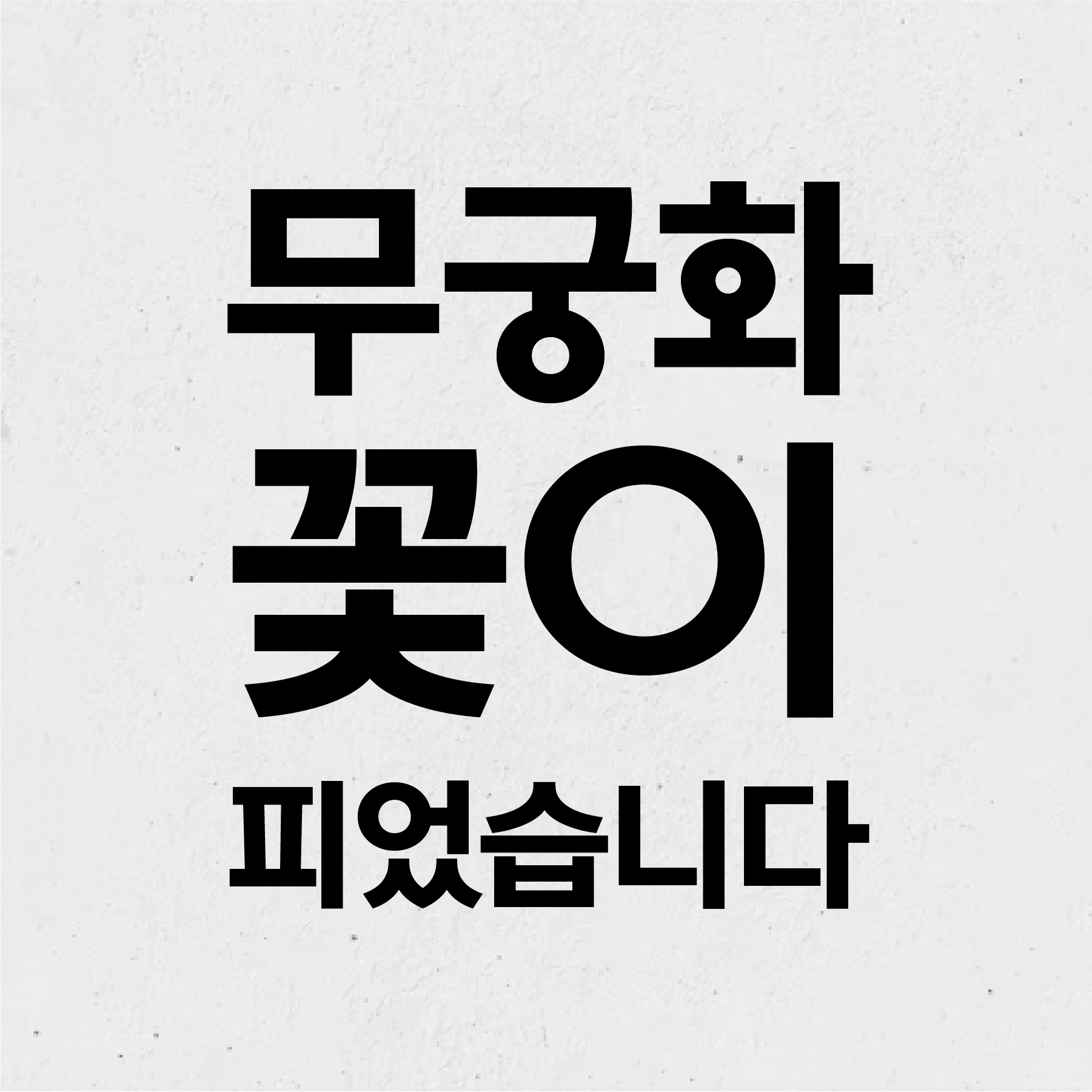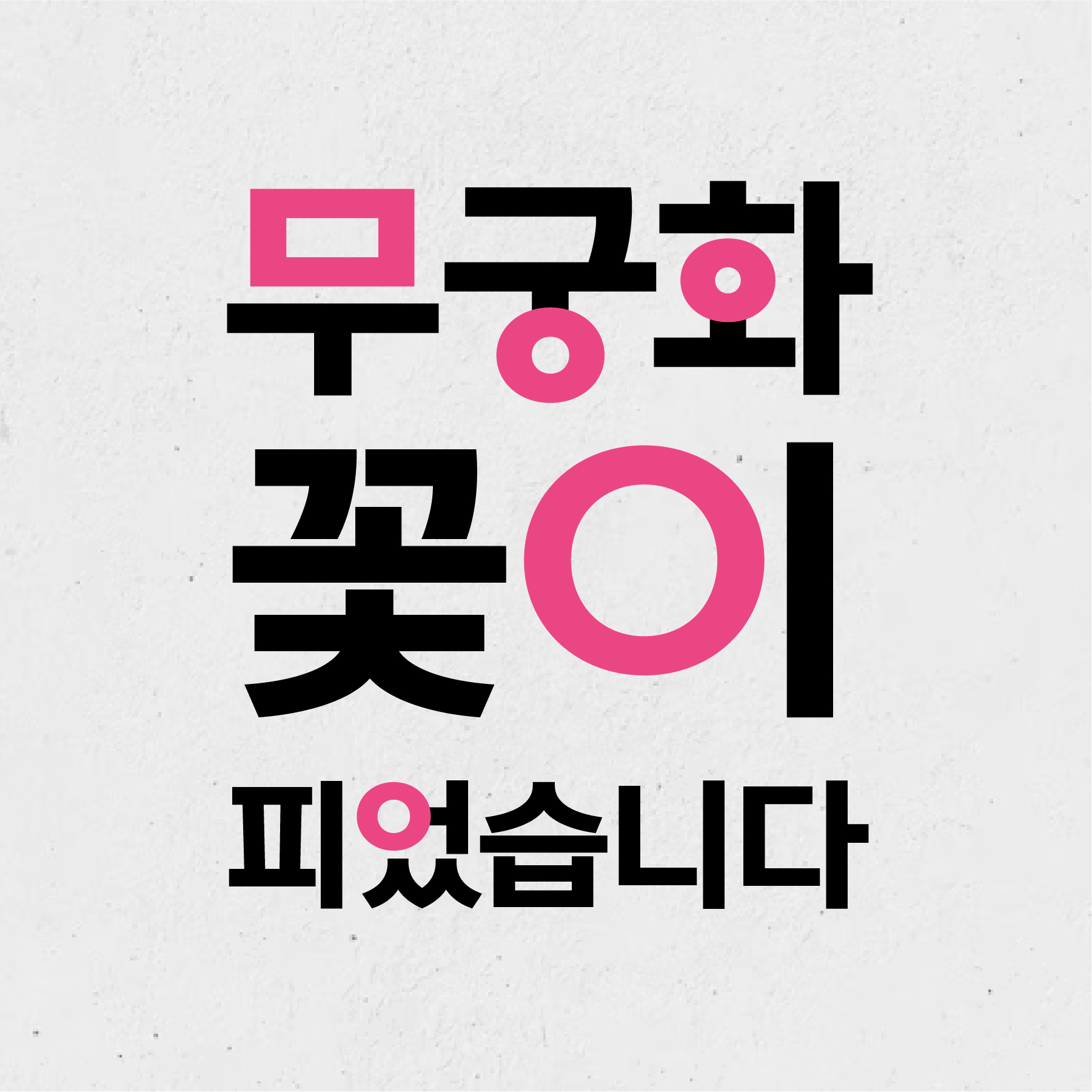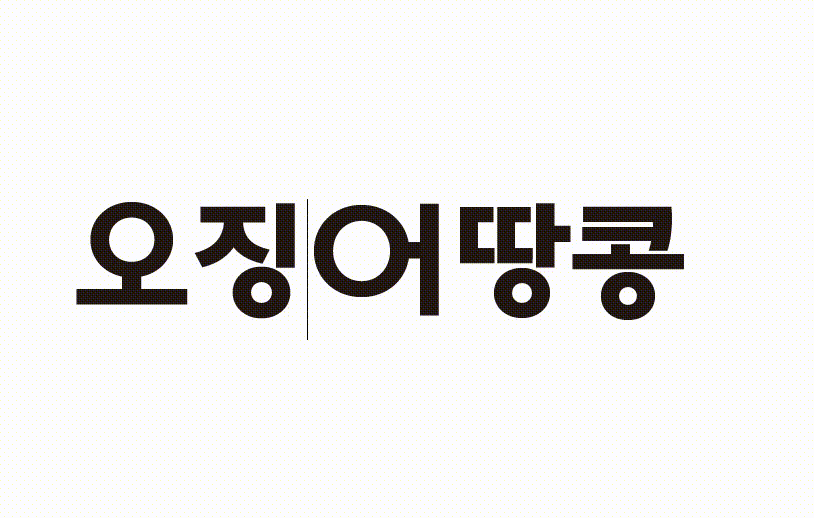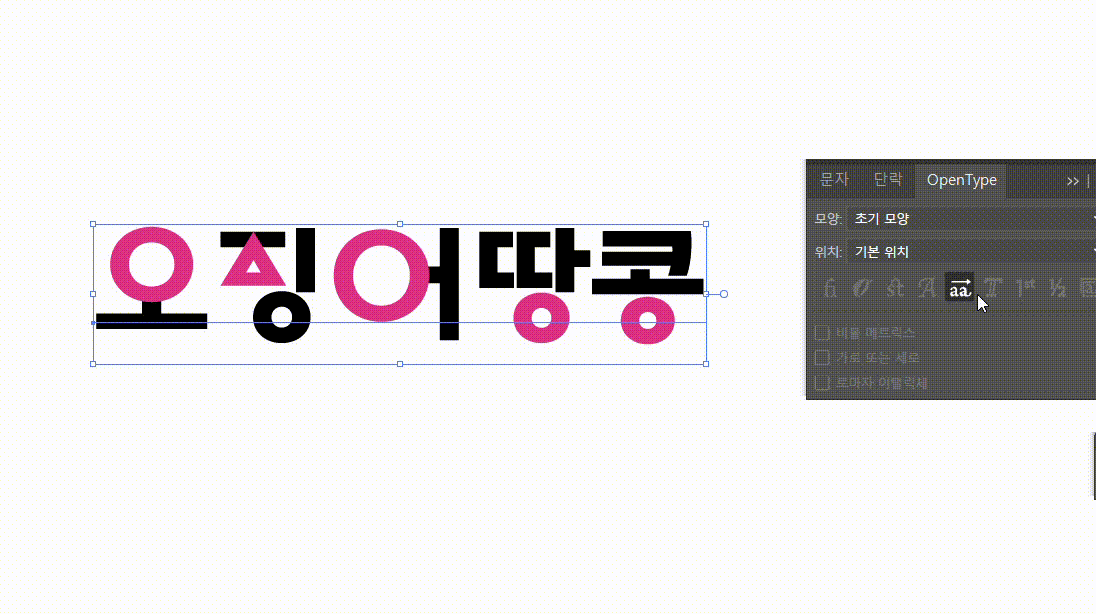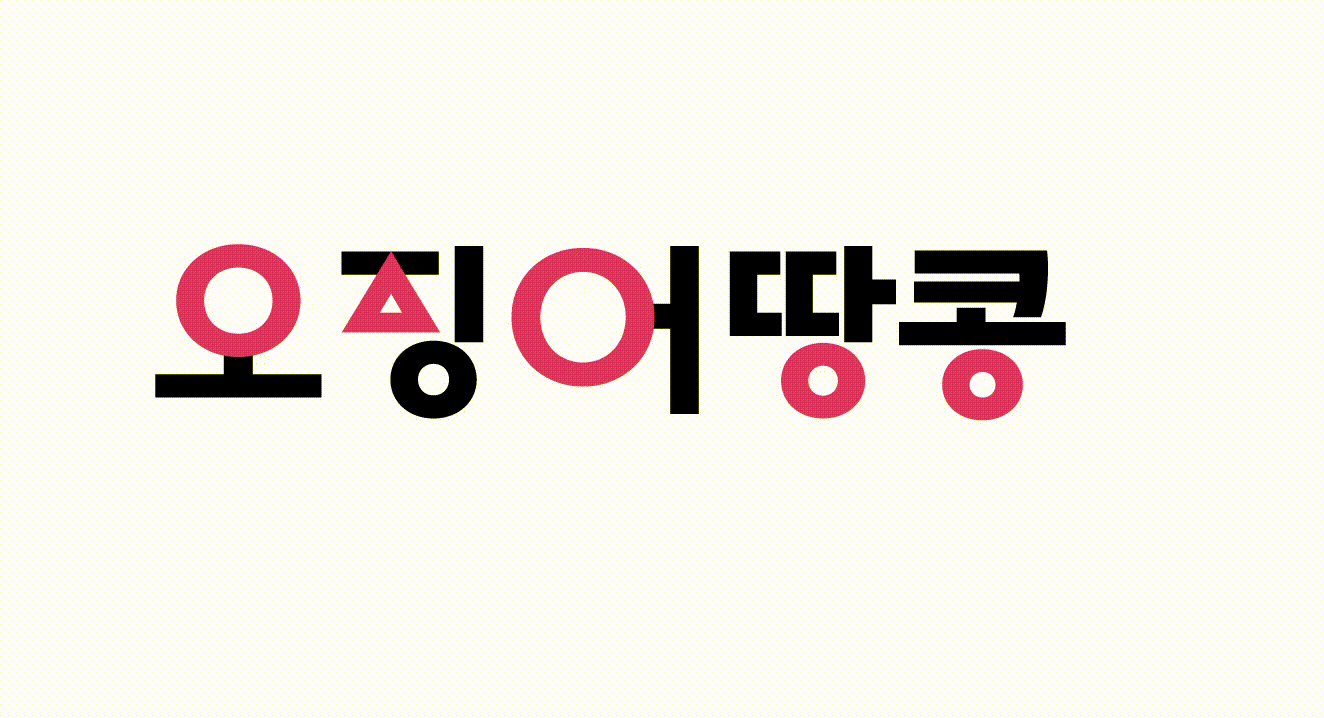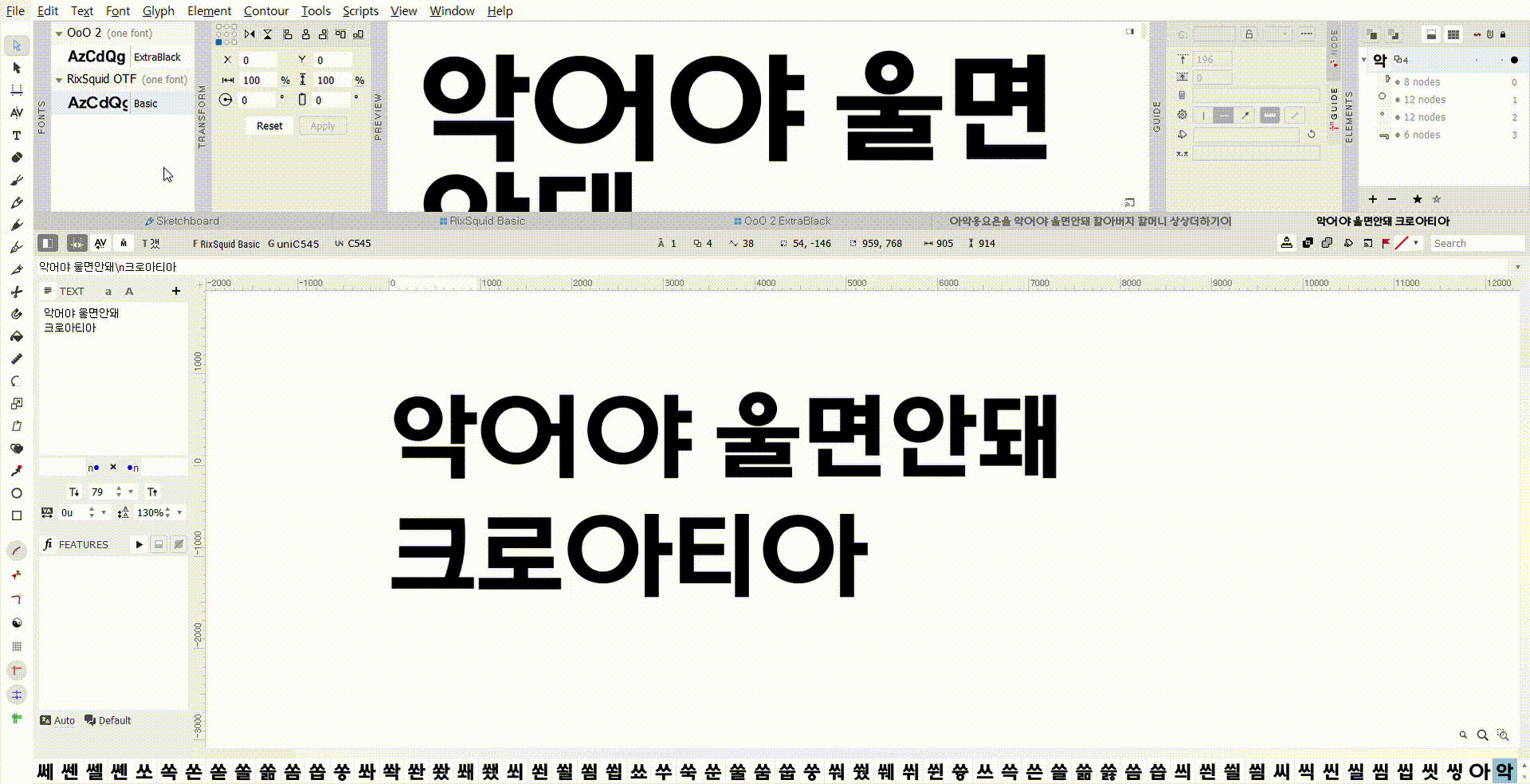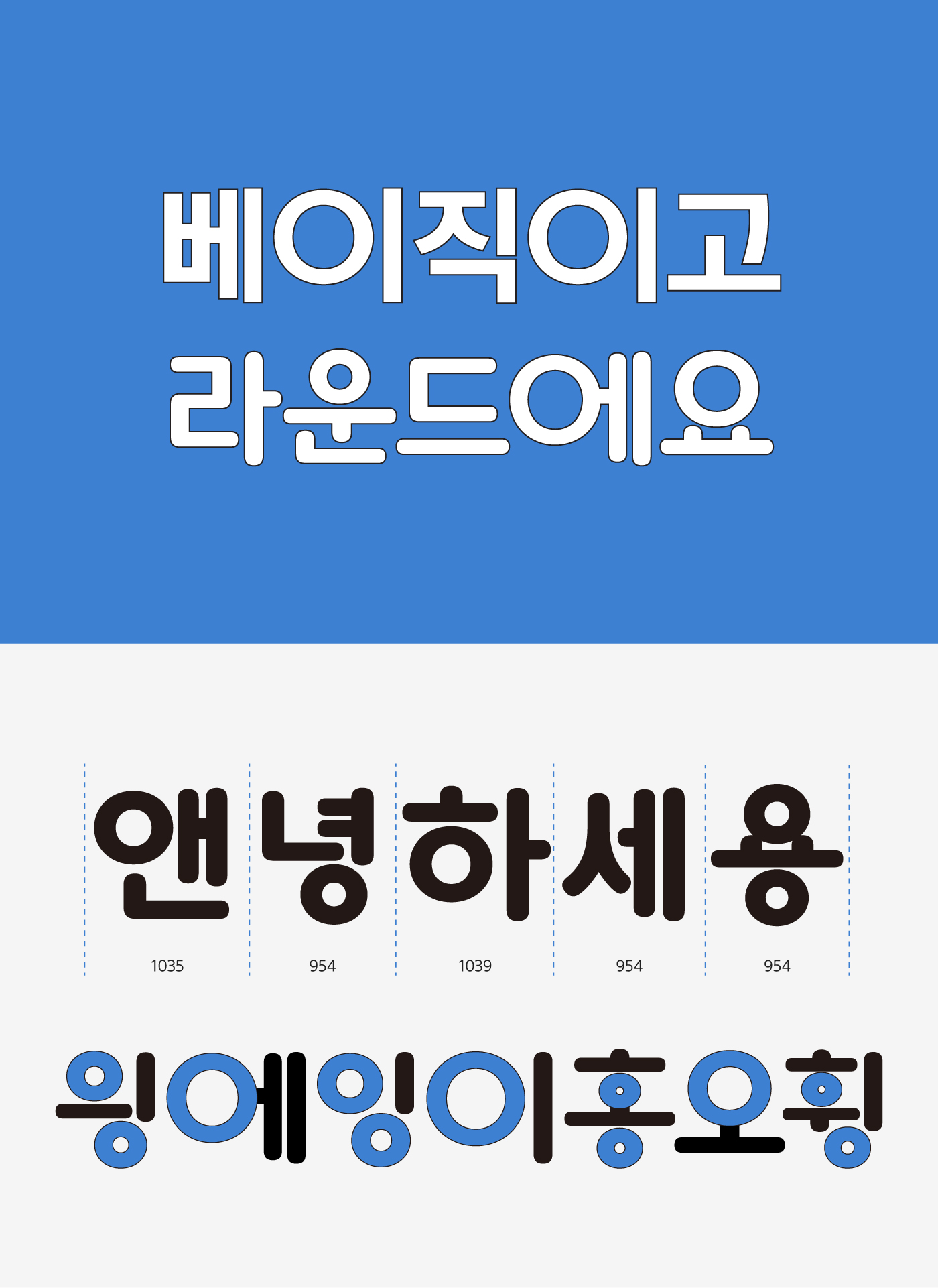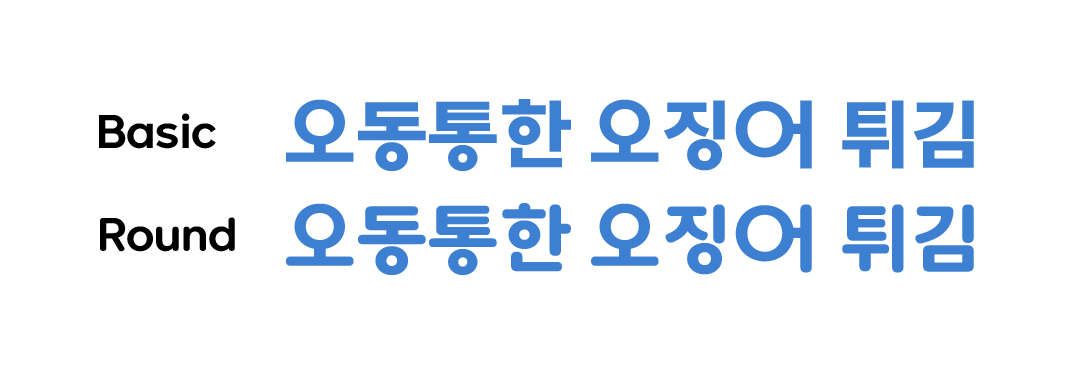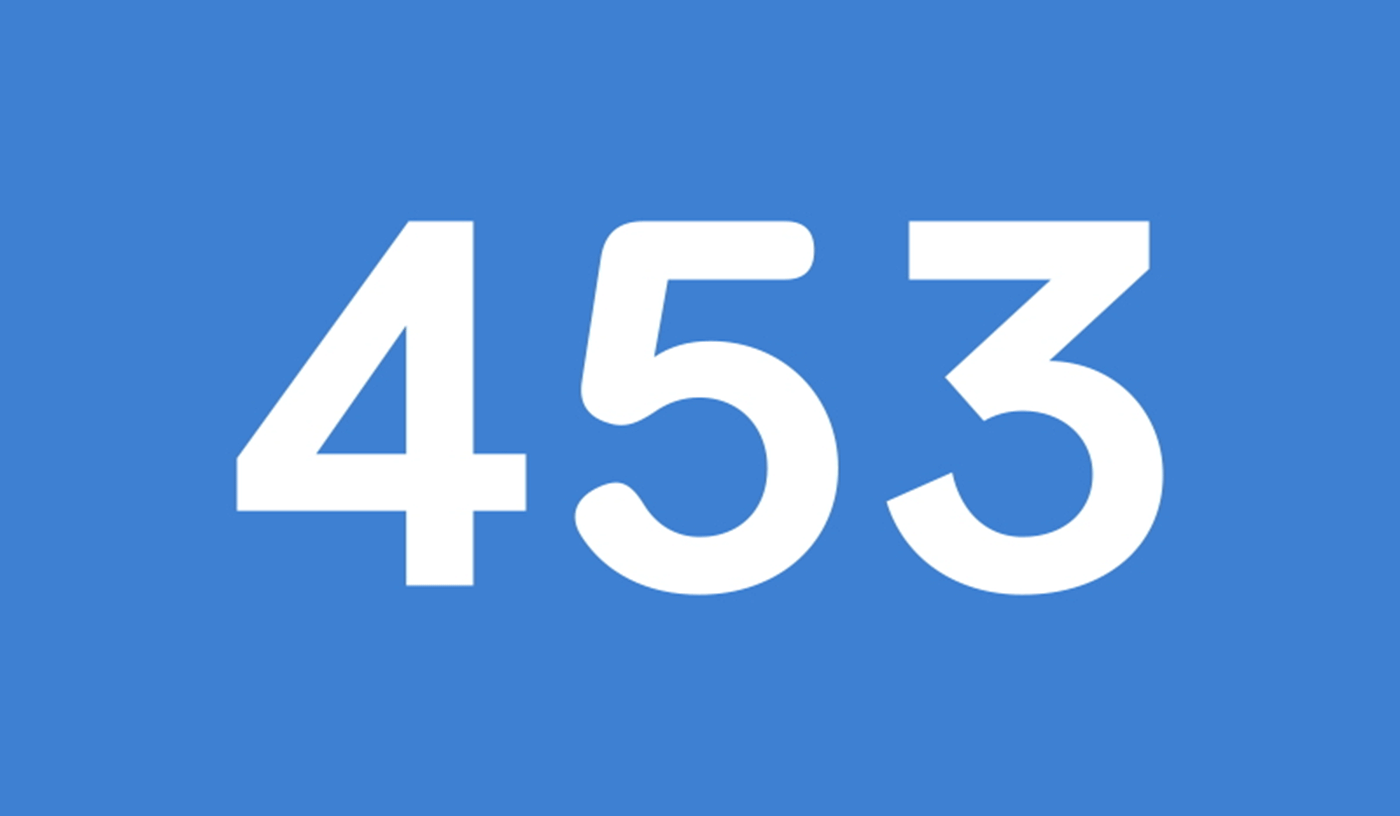
안녕하세요. 따듯해진 날씨와 함께하는 즐거운 4월의 신규 폰트 「Rix오징어」를 소개합니다. 정원 형태의 동그랗고 크고 작은 'ㅇ' 꼴이 먼저 눈에 띄는 서체인데요, 이응꼴을 중심으로 자폭과 공간이 변화하고, 동그라미, 세모, 네모 모양의 대체글립이 재미 요소로 포함된 유쾌한 폰트입니다. 이번 폰트를 제작한 윤유민 디자이너를 인터뷰를 통해 만나봤습니다 :)
Rix오징어는 어떤 폰트인가요?
정원 형태의 자소 ‘ㅇ’을 중심으로 자폭과 공간이 변화하는 서체입니다. ㅇ, ㅎ, ㅅ, ㅈ, ㅊ, ㅁ꼴에 오픈 타입을 적용해 ○, △, □ 그래픽을 손쉽게 적용할 수 있습니다.
Basic과 Round 두 가지 패밀리로 구성한 이유는?
원래 기본형만 제작하고 있었는데, ‘ㅇ’이 주된 변화 요소이다 보니 유연하고 지오그래픽적인 느낌은 라운드형에서 더 잘 어울릴 것 같아 추가 제작하게 되었습니다.
오징어게임을 오마주한 대체글립에 대해 들었어요! 좀 더 자세히 설명해 주신다면?
이번 폰트를 제작하며 느낀 점이나 배운 점이 있다면 :)
Rix오징어는 제가 처음부터 제작하지는 않고 다른 분의 작업을 이어받아 마무리하게 된 폰트인데요. 다양한 사람의 손을 거치다 보니 스타일이 통일되지 않아 하나의 폰트로 보이기 위해 정리하고 다듬는 시간을 꽤 오래가졌습니다. 그 과정에서 다른 분들의 작업 스타일이나 공간 다듬는 법 등을 보고 분석해 보면서 많이 배운 것 같아요.
깔끔한 Basic 귀여운 Round
Rix오징어는 정원 형태의 자소 ‘ㅇ’을 중심으로 자폭과 공간이 변화하는 것이 특징입니다. 글자의 너비가 각각 다른 가변폭 글꼴로 제작하여 긴 글을 썼을 때 자연스럽고 보기에 편안하도록 디자인했습니다.
글자 스타일에 따라 기본형의 깔끔한 Basic과 귀엽고 캐주얼한 Round 2가지 패밀리로 구성되었습니다.
각지고 직선적인 획으로 디자인된 베이직과 동글동글 부드러운 획이 적용된 라운드 두 가지를 모두 사용하여 다양한 콘텐츠에 활용할 수 있습니다. 숫자, 영문, 일문, 약물에도 동일한 특징이 적용되어 있어 혼용 시 조화롭게 쓸 수 있어요🪄
재미있는 그래픽 효과🦑
이번 서체의 재밌는 포인트는요. ㅇ, ㅎ, ㅅ, ㅈ, ㅊ, ㅁ이 들어간 글자들을 타이핑 후 드래그해서 대체글립을 적용하면 특정 컬러가 들어간 ○, △, □ 그래픽이 표현된다는 점! 이렇게 색다른 표현을 손쉽게 적용할 수 있습니다.(위쪽 인터뷰에서 자세한 적용 방법을 확인해 보세요😉)
이렇게 활용해 보세요🌸
이벤트 팝업 배너, 웹디자인, 포스터 디자인 등 봄기운 가득한 밝고 컬러풀한 콘텐츠에 딱 좋은 Rix오징어 Round! 귀여우면서도 부드러운 이미지로 텍스트가 눈에 잘 들어와요.
명함 등 좀 더 담백하고 정돈된 디자인에는 Basic을 활용하여 돋보이게 제작할 수 있습니다. 전문성을 나타내기에 좋은 깔끔하고 단정한 이미지도 갖고 있어요.